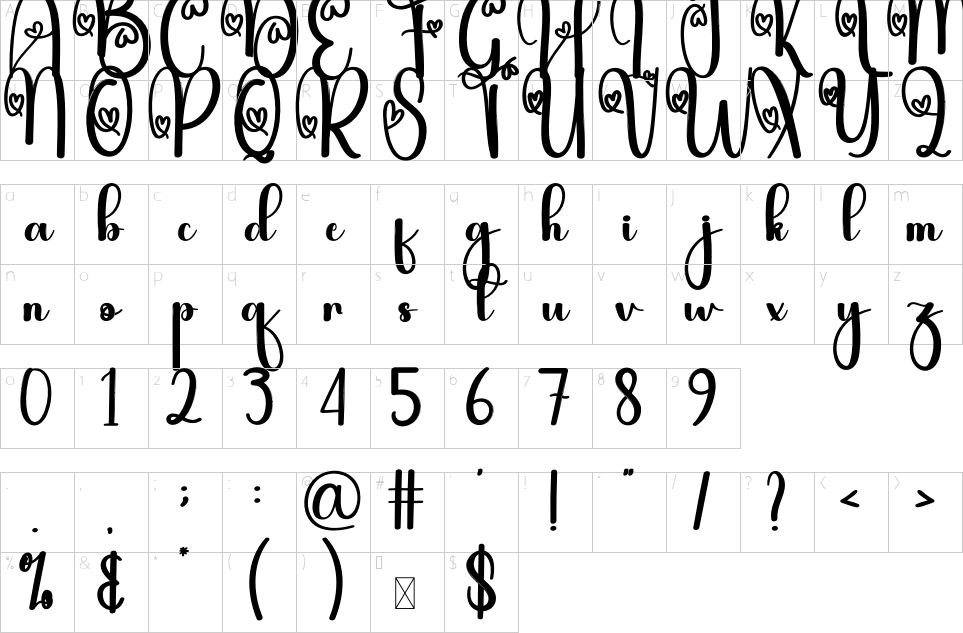
A fonte Samantha oferece um estilo elegante e moderno que se encaixa perfeitamente em diversos projetos digitais. Desenvolvida por William Jhordy, esta fonte é uma excelente opção para quem procura uma solução gráfica versátil e confiável. Com seu design cuidadosamente desenvolvido, a Samantha se destaca não apenas em design gráfico, mas também em criação de websites e publicações digitais. Com a facilidade de download gratuito e instantâneo da 1001 Free Fonts, você pode experimentar a Samantha para personalizar documentos, banners, logotipos e muito mais. Com seu design fluido e atraente, a Samantha se torna uma escolha inteligente para qualquer designer ou criativo buscando um recurso gráfico eficaz para seus projetos.